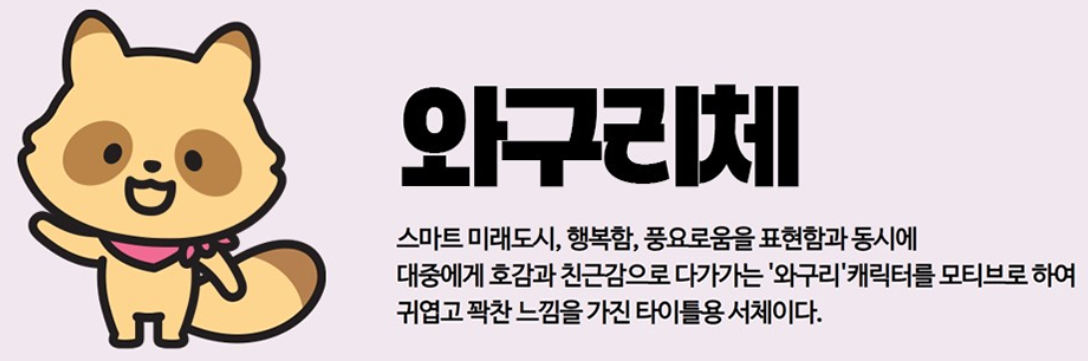
| 폰트명 | 와구리체 |
| 주요 활용 | SNS 글꼴, 포스터, 초대장, 브랜딩, 문서 디자인 |
👉 부드러운 곡선과 손글씨 감성이 강조된 무료 한글 폰트입니다.
2. 와구리체 특징
- 손글씨 감성: 따뜻하고 아기자기한 느낌 전달 ✍️
- 부드러운 곡선: 가독성 높고 시각적으로 편안함 제공
- 다양한 활용성: SNS, 포스터, 문서, 카드뉴스 등 폭넓게 사용 가능
4. 와구리체 활용 예시
| 활용 분야 | 설명 |
|---|---|
| SNS 포스팅 | 감성적인 메시지를 전달하는 글꼴로 적합 |
| 포스터 디자인 | 아기자기한 분위기를 살려주는 시각적 효과 |
| 초대장 제작 | 웨딩, 행사 초대장에 따뜻한 분위기 연출 |
| 브랜딩 작업 | 브랜드 감성을 표현할 때 차별화된 개성 제공 |
👉 단순 문서부터 디자인 프로젝트까지 활용 범위가 넓습니다.
5. 와구리체 사용 팁
- 카카오톡, 블로그, SNS 글에 적용하면 독창적인 분위기를 연출할 수 있습니다.
- 문서 작업 시 제목용, 포스터나 카드뉴스 제작 시 본문과 조합하면 효과적입니다.
- 색상·배경과 함께 활용하면 디자인 완성도가 높아집니다. 🎨